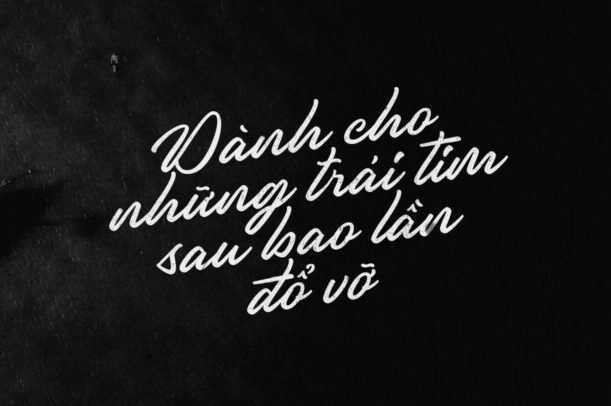
Khám Phá Vẻ Đẹp Quyến Rũ Của Font Việt hóa MTD Fancy Melody
Phông chữ là linh hồn của thiết kế. Trong kho tàng phong phú của thế giới typographic, sự xuất hiện của Font Chữ nghệ thuật luôn mang đến một làn gió mới, đặc biệt là các phông chữ được Việt hóa hoàn chỉnh. Hôm nay, chúng ta sẽ cùng đi sâu vào tìm hiểu một cái tên đang làm mưa làm gió trong cộng đồng thiết kế: Font Việt hóa MTD Fancy Melody. Đây không chỉ là một phông chữ đẹp mắt với nét viết tay mềm mại, mà còn là công cụ đắc lực giúp các bạn học sinh, sinh viên và giáo viên tạo ra các ấn phẩm, bài giảng, hoặc thiệp mời mang tính thẩm mỹ cao. Phong cách bay bổng, lãng mạn của MTD Fancy Melody đã chinh phục hàng triệu người dùng, từ những nhà thiết kế chuyên nghiệp cho đến các bạn trẻ đang chuẩn bị cho kỳ thi tốt nghiệp quan trọng, muốn tạo ra những kỷ niệm đáng nhớ. Việc sử dụng phông chữ nghệ thuật, được tối ưu hóa cho tiếng Việt, là chìa khóa để nội dung trở nên hấp dẫn và chuyên nghiệp hơn.
Font Việt hóa MTD Fancy Melody – Sự Lựa Chọn Hoàn Hảo Cho Thiết Kế Việt
Điều gì khiến Font Việt hóa MTD Fancy Melody trở nên đặc biệt? Điểm mạnh lớn nhất của phông chữ này chính là sự kết hợp hài hòa giữa phong cách viết tay (script font) lãng mạn và tính năng hỗ trợ ngôn ngữ Việt Nam hoàn chỉnh. MTD Fancy Melody mang nét chữ thanh mảnh ở đầu và cuối, nhưng lại có độ đậm vừa phải ở thân chữ, tạo nên sự tương phản thú vị và dễ đọc. Sự “Fancy” trong tên gọi thể hiện rõ qua các đường cong mềm mại, các nét nối liền mạch như một dòng chảy âm nhạc. Phông chữ này rất phù hợp để sử dụng trong các dự án đòi hỏi tính cá nhân hóa và nghệ thuật cao, chẳng hạn như thiết kế logo cá nhân, trang trí bìa sổ lưu niệm cuối cấp, hay các dự án đồ họa mang tính giáo dục nhẹ nhàng.
Đối với các bạn học sinh, đặc biệt là các bạn cuối cấp đang lên ý tưởng cho cuốn kỷ yếu hoặc thiệp mời dự lễ tốt nghiệp, việc sử dụng MTD Fancy Melody sẽ mang lại cảm giác hoài niệm và trang trọng. Phông chữ này không chỉ đơn thuần là hiển thị văn bản mà còn truyền tải cảm xúc. Việc đã được Việt hóa kỹ lưỡng đảm bảo rằng tất cả các dấu tiếng Việt (như sắc, huyền, hỏi, ngã, nặng, và các ký tự đặc biệt) đều hiển thị chính xác và mượt mà, loại bỏ hoàn toàn lỗi font thường gặp khi sử dụng các font quốc tế chưa được tối ưu hóa. Điều này cực kỳ quan trọng đối với các tài liệu học thuật và các văn bản chính thức được sử dụng trong môi trường giáo dục.
Phông chữ đẹp luôn là yếu tố quan trọng giúp thu hút sự chú ý. Nhà thiết kế hay các thầy cô giáo thường xuyên tìm kiếm các font chữ nghệ thuật để làm mới bài giảng điện tử (e-learning) hoặc các poster thông báo sự kiện trường học. MTD Fancy Melody với sự bay bổng của mình đã trở thành một tài sản quý giá, giúp các ấn phẩm này nổi bật hơn hẳn so với việc sử dụng các phông chữ tiêu chuẩn nhàm chán như Times New Roman hay Arial. Hơn nữa, phông chữ này tương thích tốt trên nhiều nền tảng phần mềm đồ họa phổ biến như Adobe Photoshop, Illustrator, và thậm chí là các công cụ văn phòng như Microsoft Word và PowerPoint, giúp mọi người dễ dàng tiếp cận và sử dụng.
Tính Năng Việt Hóa và Ứng Dụng Thực Tiễn Trong Giáo Dục và Đồ Họa
Một trong những lý do khiến cộng đồng thiết kế Việt Nam yêu thích MTD Fancy Melody là bởi tính năng Việt hóa toàn diện. Quá trình Việt hóa không chỉ là thêm các dấu, mà còn là căn chỉnh kerning và spacing sao cho các từ tiếng Việt không bị rời rạc hoặc khó đọc khi sử dụng các ký tự có dấu phức tạp. Nhờ đó, phông chữ này duy trì được vẻ đẹp mỹ thuật của mình ngay cả khi được áp dụng cho các đoạn văn bản dài. Ứng dụng của MTD Fancy Melody trong lĩnh vực giáo dục là vô cùng đa dạng. Giáo viên có thể sử dụng nó để thiết kế các chứng chỉ, bằng khen điện tử, hay tạo tiêu đề cho các slide bài giảng sinh động, đặc biệt là các môn học thiên về nghệ thuật, văn học, hoặc các hoạt động ngoại khóa.
Đối với học sinh cấp 3 sắp bước vào kỳ thi tốt nghiệp, việc chuẩn bị các món quà lưu niệm, thiệp cảm ơn thầy cô giáo cũng là một phần không thể thiếu. Sử dụng MTD Fancy Melody cho phép tạo ra những thông điệp cá nhân hóa, thể hiện sự trân trọng một cách tinh tế. Đây là một phông chữ “cảm xúc”, rất thích hợp cho các lời chúc ý nghĩa. Ngoài ra, phông chữ này cũng rất được ưa chuộng trong ngành thiết kế thiệp cưới, poster sự kiện, và các ấn phẩm liên quan đến phong cách vintage hoặc handmade. Sự linh hoạt này giúp MTD Fancy Melody trở thành một trong những phông chữ nghệ thuật Việt hóa được tìm kiếm nhiều nhất trên các công cụ tìm kiếm.
Tóm lại, Font Việt hóa MTD Fancy Melody là một tài nguyên thiết kế đáng giá, mang lại sự tinh tế và cá nhân hóa cho mọi dự án. Từ các bài tập sáng tạo của học sinh, các ấn phẩm truyền thông của trường học, cho đến những thiết kế đồ họa chuyên nghiệp, phông chữ này đều thể hiện được giá trị vượt trội của mình. Nó không chỉ giải quyết được vấn đề hiển thị tiếng Việt mà còn nâng cao tính thẩm mỹ tổng thể của nội dung.